Угловые скобки ⟨ ⟩ в рукописном шрифте: форма и проверка
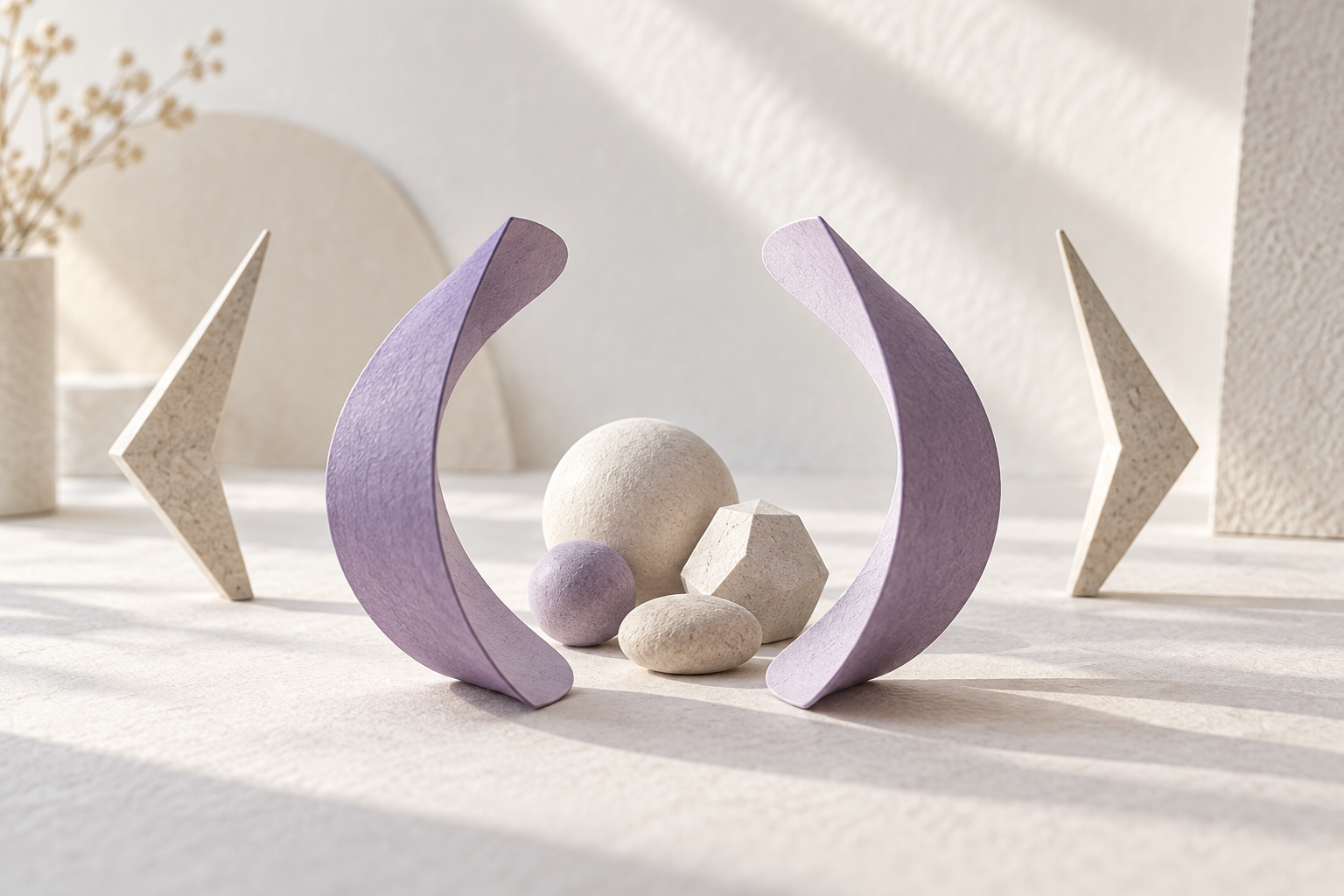
Математические угловые скобки ⟨ и ⟩ — отдельная парная пунктуация для формул и обозначений. Их не следует подменять знаками меньше и больше < и >: похожий контур не означает одинаковый знак. Чтобы пара работала в рукописном шрифте, проверьте кодовые точки U+27E8 и U+27E9, постройте зеркально согласованные формы и испытайте их в формулах, словесных примерах и при разных размерах.
Чем ⟨ ⟩ отличаются от < и >
В Unicode символы U+27E8 и U+27E9 называются MATHEMATICAL LEFT ANGLE BRACKET и MATHEMATICAL RIGHT ANGLE BRACKET. Они предназначены для математических угловых скобок; в типичных примерах пара окружает выражение или объект. Знаки < и > — это U+003C LESS-THAN SIGN и U+003E GREATER-THAN SIGN, которые в математическом тексте обычно участвуют в сравнении, а в разметке могут иметь синтаксическое значение. Стандарт отдельно перечисляет эти символы, поэтому визуальное сходство не повод кодировать одну пару вместо другой.
Практический пример: запись ⟨x, y⟩ может обозначать упорядоченную пару или скалярное произведение в конкретной математической нотации; запись x < y читается как сравнение. Смысл зависит от дисциплины и контекста, поэтому не нужно приписывать самой паре скобок одно универсальное значение. Задача гарнитуры проще и важнее: каждый знак должен оставаться различимым, а закрывающая скобка — действительно закрывать выражение.
Не смешивайте их также с кавычками-ёлочками « » и одиночными угловыми кавычками ‹ ›. У этих знаков другое назначение и свой рисунок. Если проект включает математическую и редакционную пунктуацию, каждой паре нужны отдельные ячейки в наборе и отдельная проверка: похожие диагонали могут быстро сблизиться в маленьком кегле.
Сначала решите, где пара будет использоваться
До рисования соберите короткий перечень задач: формулы, учебные карточки, словарь терминов, научно-популярный текст, запись в интерфейсе или подписи к данным. Достаточно тех сценариев, ради которых включаете знаки в гарнитуру. Контекст подскажет, должны ли скобки выглядеть как компактная математическая пара, поддерживать выразительный рукописный почерк или спокойно работать рядом с кириллицей и цифрами.
Найдите 5–10 реальных образцов из материалов проекта, не копируя чужой шрифт. Выпишите содержимое между скобками: одиночную букву, двузначное выражение, букву с индексом, дробь, вектор или короткую подпись. На первом этапе это не тест абсолютной математической корректности, а способ определить, что именно читатель должен быстро увидеть: границу выражения, парность знаков и положение скобок относительно соседей.
Как построить форму и сохранить почерк
Определите высоту и оптический центр
Обе скобки должны охватывать обычную высоту выражения, но не обязаны повторять высоту заглавной буквы. Сверьте верхний и нижний концы с цифрами, строчными знаками и высокими элементами вашей гарнитуры. Если скобки применяются с индексами или компактными формулами, убедитесь, что короткий знак не кажется случайной запятой, а высокий не перетягивает внимание на себя.
В рукописном стиле удобнее сначала сделать направляющие: линия верхнего конца, базовая линия и линия нижнего конца. Набросайте левую скобку одним уверенным движением; затем отразите принцип движения для правой, сохраняя характер окончания штриха. Механально переворачивать контур не обязательно: направление пера, наклон и входной штрих могут требовать осмысленной коррекции. Важно, чтобы пара воспринималась парой, а не двумя случайно подобранными знаками.
Настройте угол, кривизну и окончания
Слишком острый внутренний угол превращает скобку в стрелку или знак сравнения. Слишком пологая диагональ делает пару похожей на косые черты. Начните с простого ломаного или мягко изогнутого контура, затем проверьте его в строке, а не только отдельно. Концы должны ясно показывать направление внутрь выражения; одинаково тупые завершения у всех штрихов часто дают тяжёлый, плохо различимый силуэт.
Свяжите толщину штриха с остальной пунктуацией и математическими знаками. Если в шрифте есть скобки круглые и квадратные, поставьте рядом четыре семейства: ( ), [ ], ⟨ ⟩, { }. Угловая пара не должна случайно оказаться заметно тоньше круглой или массивнее фигурной. Сравнивайте не только центральный штрих, но и то, как законченные знаки выглядят при одинаковом масштабе.
Сделайте зеркальную пару, а не копию
Левая и правая скобки обязаны взаимно обрамлять выражение. Для черновика полезно отразить один контур, чтобы проверить общую ширину и наклон. После этого поправьте ручные особенности: чуть разную массу верхнего и нижнего окончания, характер входа пера, оптический вынос. В итоге пару должно быть удобно читать слева направо; если правая скобка визуально повторяет левую, знак будет смотреть внутрь не так, как ожидается.
Математические угловые скобки требуют и хорошего рисунка, и правильного кодирования: один критерий не компенсирует другой. Сделайте парные глифы согласованными с почерком, различимыми рядом со знаками < и > и проверенными на реальных формулах до экспорта. Для своего набора рукописных символов можно начать с создания шаблона на Fontgenerator.ru и включить эту пару в контрольный лист проекта.